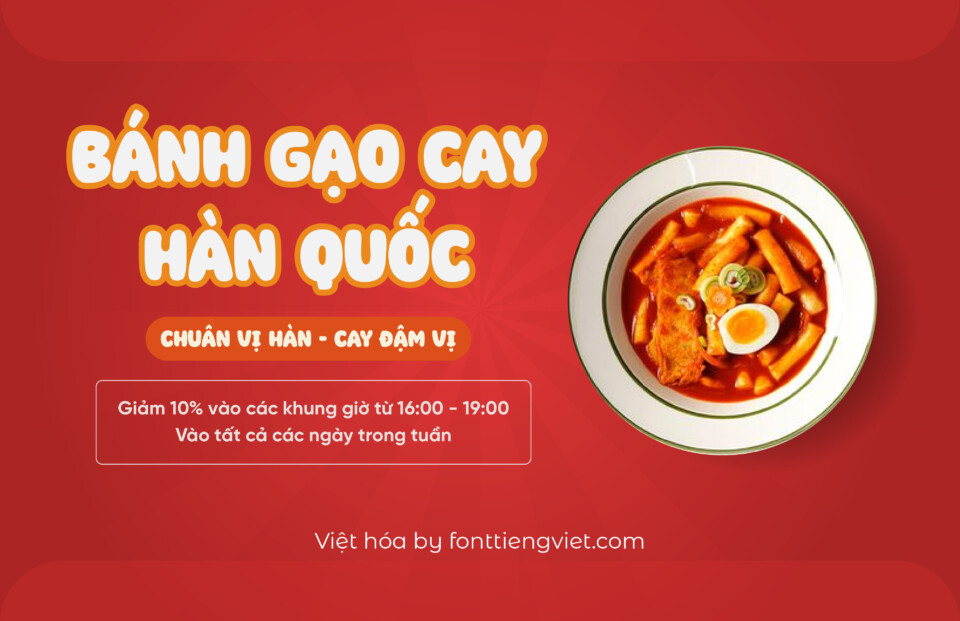
Font Việt hóa 1FTV VIP Super Foods
Giới thiệu bộ Font Việt hóa 1FTV VIP Super Foods
Trong thế giới thiết kế đồ họa hiện đại, việc tìm kiếm một bộ chữ vừa mang tính thẩm mỹ cao vừa hỗ trợ đầy đủ tiếng Việt là điều vô cùng quan trọng. Bộ Font Việt hóa 1FTV VIP Super Foods chính là giải pháp hoàn hảo dành cho các bạn học sinh và giáo viên khi muốn tạo ra những ấn phẩm học tập sinh động. Đây là một mẫu Font Miễn Phí có phong cách viết tay trẻ trung, đường nét mềm mại và đầy sự sáng tạo. Font chữ này không chỉ giúp bài thuyết trình thêm phần bắt mắt mà còn tạo cảm giác gần gũi, thân thiện đối với người xem ngay từ cái nhìn đầu tiên.
Đặc điểm nổi bật của Font Việt hóa 1FTV VIP Super Foods
Thiết kế hiện đại và linh hoạt
Điểm mạnh nhất của Font Việt hóa 1FTV VIP Super Foods nằm ở cấu trúc chữ cân đối và các ký tự được chăm chút tỉ mỉ. Bộ font này đặc biệt phù hợp cho các dự án thiết kế bao bì thực phẩm, poster sự kiện trường học hoặc menu quán nước. Nhờ việc đã được Việt hóa kỹ lưỡng, bạn sẽ không gặp lỗi dấu khi soạn thảo văn bản, giúp quy trình làm việc trở nên trơn tru và chuyên nghiệp hơn rất nhiều.
Ứng dụng đa dạng trong học tập
Các em học sinh có thể sử dụng bộ chữ này để trang trí báo tường, làm thiệp chúc mừng hoặc thiết kế các trang bìa vở cá nhân. Sự kết hợp giữa nét chữ nghệ thuật và tính ứng dụng cao giúp cho mọi ý tưởng sáng tạo đều trở nên nổi bật và ấn tượng hơn bao giờ hết.